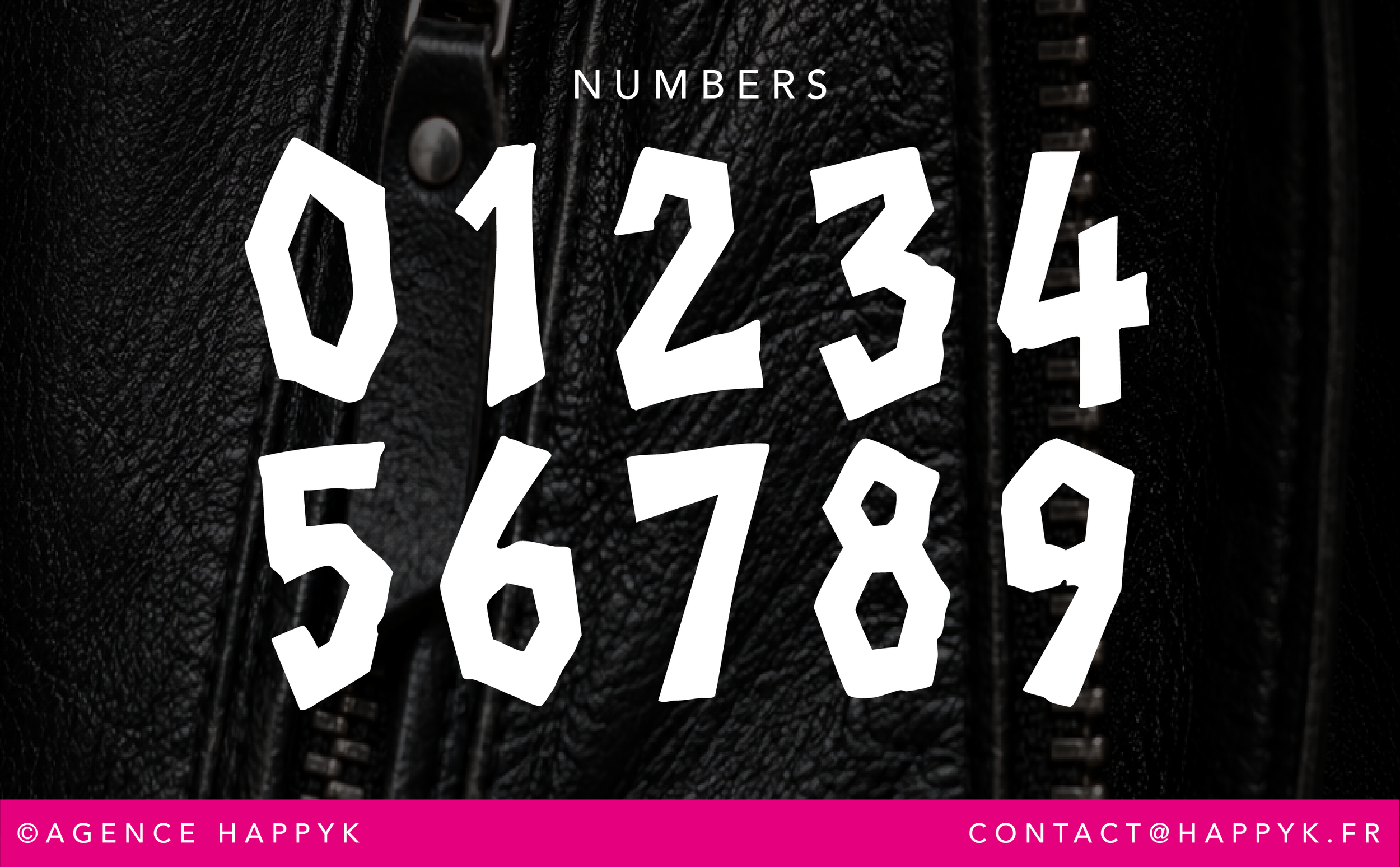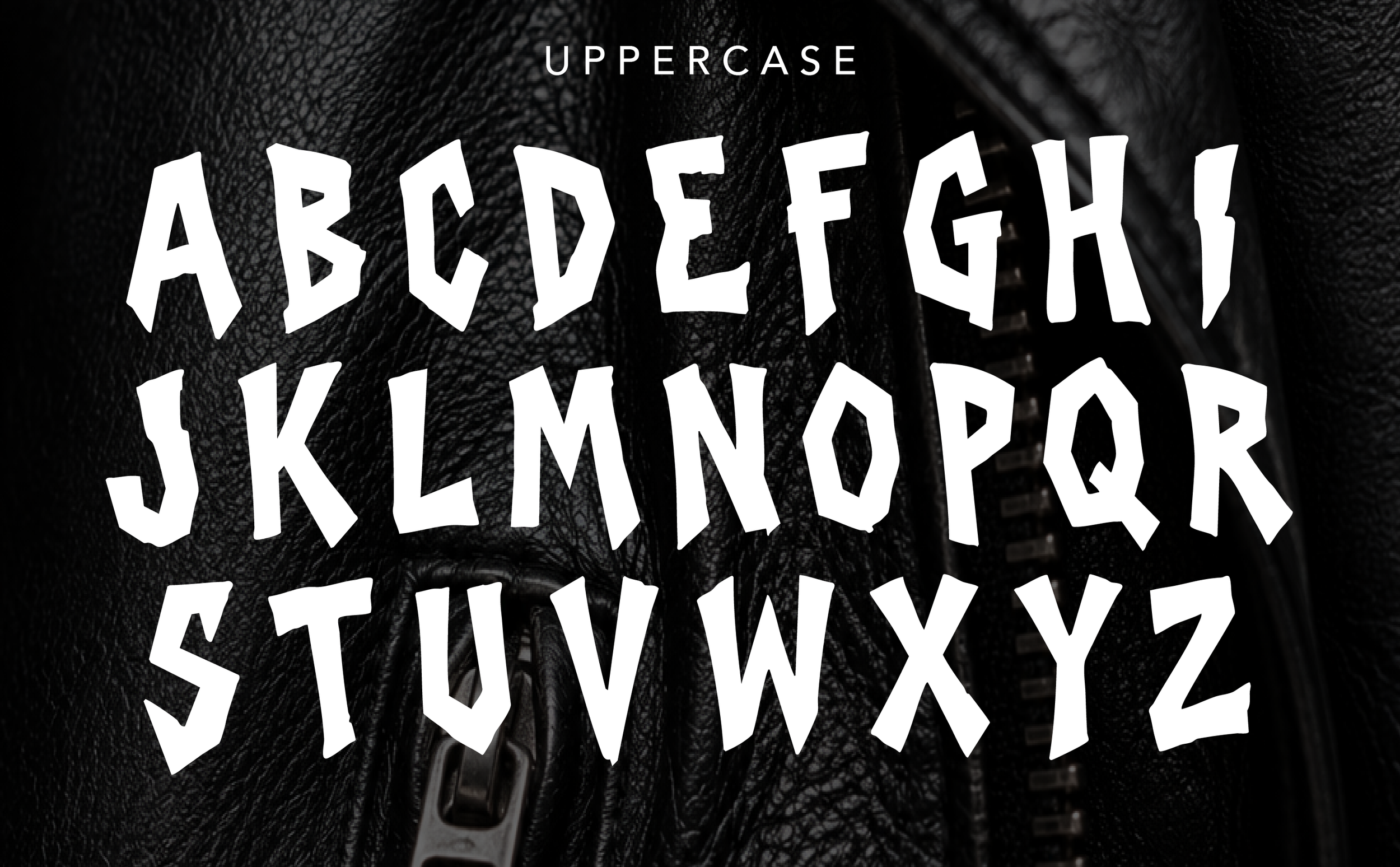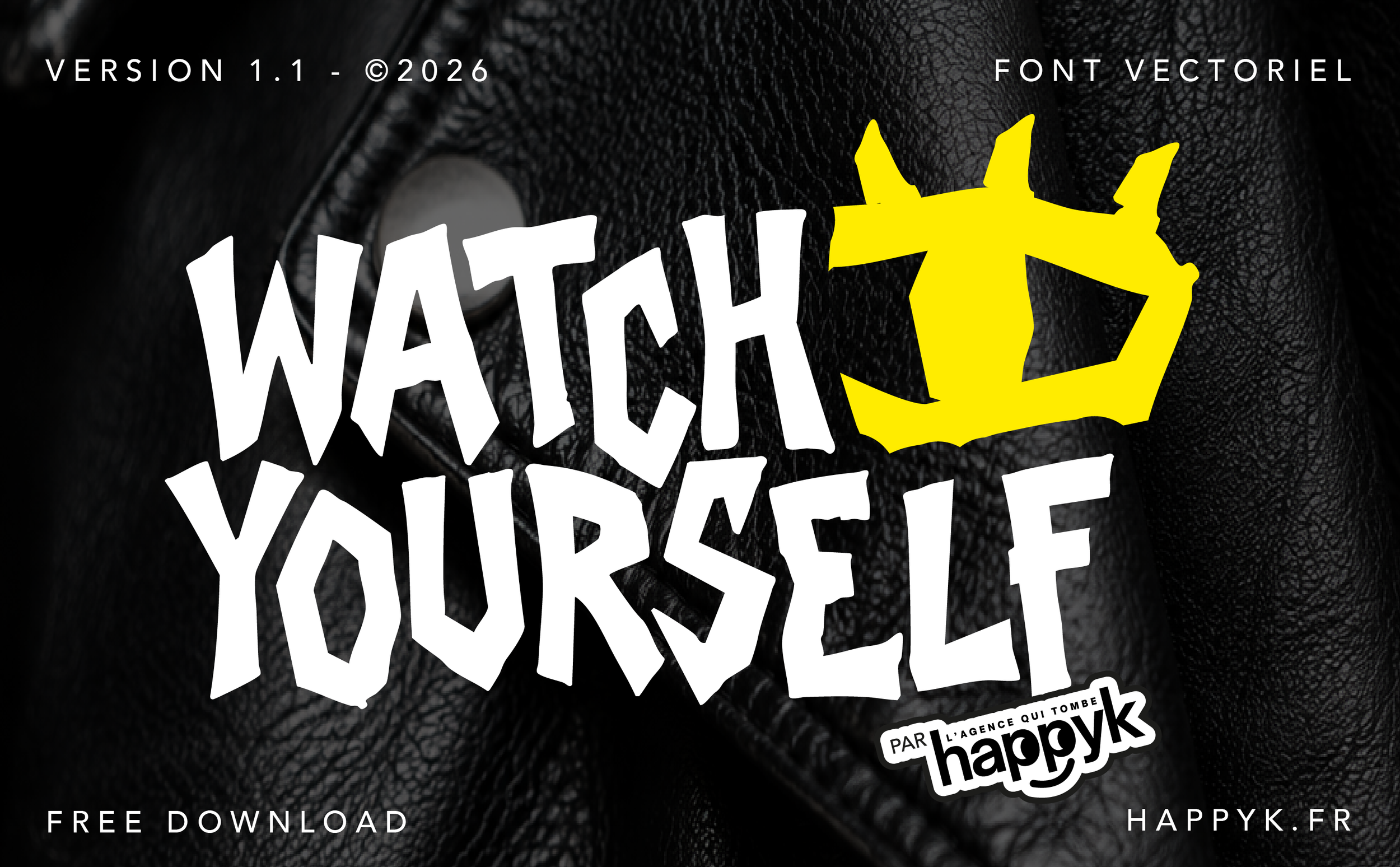
WATCH YOURSELF
Watch Yourself Une typo qui ne demande pas la permission.
Inspirée de la scène punk, du skate et des affiches underground, Watch Yourself mise sur l’imperfection, l’énergie et l’attitude. Ses formes anguleuses et irrégulières donnent immédiatement du caractère à vos titres, logos et affiches.
Pensée pour les projets qui veulent faire du bruit plutôt que de passer inaperçus. Brute. Directe. Sans filtre. 🤘🖤